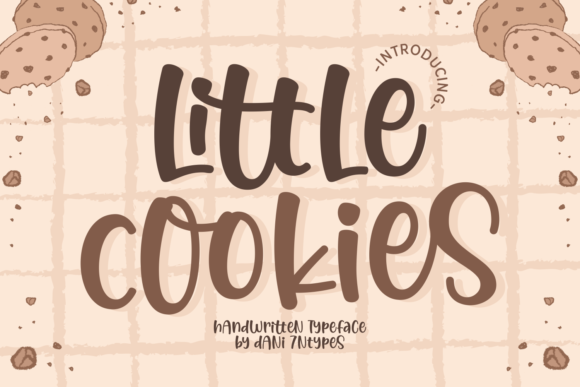
Little Cookies Font
Little Cookies Font – خط أنيق وجذاب يجمع بين الطابع المرح واللمسة الإبداعية، مثالي للمشاريع التي تحتاج إلى لمسة دافئة وحيوية. يتميز الخط بتصميم فريد يمنح نصوصك طابعًا مميزًا، مما يجعله مثاليًا لتصميمات العلامات التجارية، والتغليف، والبطاقات، والمطبوعات، والمشاريع الرقمية.